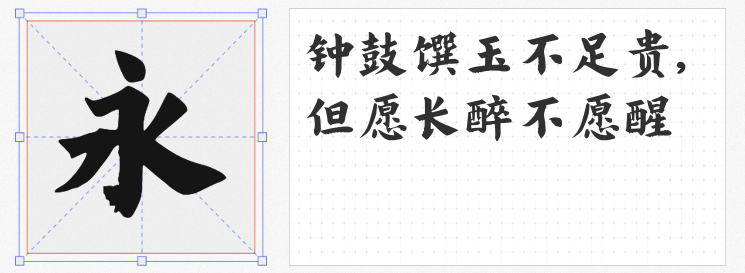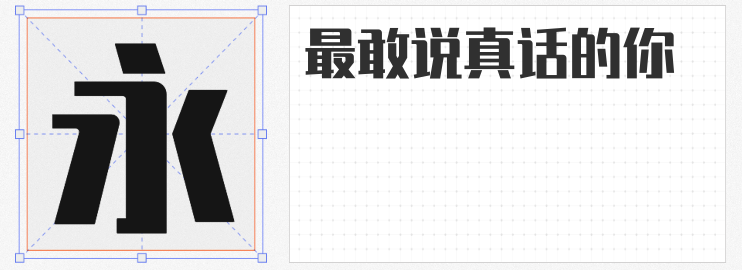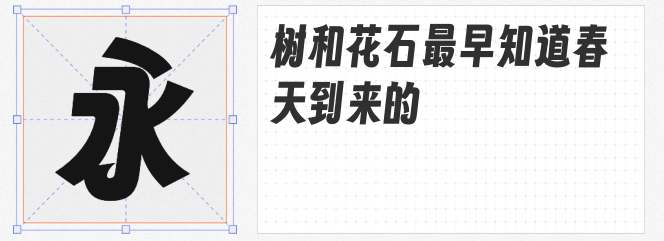
在短视频与媒体内容竞争激烈的今天,一个吸引眼球的封面设计往往能决定内容的点击率与传播力。而字体,作为封面设计中的灵魂元素,其选择至关重要。今天,我们精心挑选了四款既免费商用又极具创意的字体,助你轻松打造出令人过目难忘的封面作品。
这款字体笔触浑厚,笔画曲折有致,个性鲜明而不失刚柔并济之美。直角与圆角的巧妙搭配,让字体在婉转中透露出落落大方的气质,非常适合用于需要展现力量感与现代感的封面设计。
2. 乡立方黑体
灵感源自乡村发展的时代感刷墙字体,乡立方黑体在保留乡村韵味的同时,融入了现代设计理念。它通过对笔形、部件及字面空间的创新设计,构建出了一款既符合乡村形象又具时代感的全新字体,为乡村主题内容的封面设计提供了独特选择。
3. 程荣光刻楷
作为一款免费商用的楷体字体,程荣光刻楷以其工整秀丽、韵味悠长的特点,赢得了众多设计师的青睐。它适用于需要展现文化底蕴与雅致氛围的封面设计,让内容在传递信息的同时,也能感受到一份来自书法的宁静与美好。
4. 字魂扁桃体
基于得意黑进行创意升级,字魂扁桃体在保留得意黑标志性倾斜与弯弧处理的基础上,通过加粗字重、加宽字身以及特色喇叭口设计,让字体更加饱满有力,个性十足。这款字体既温和又时髦,非常适合用于追求时尚感与创意表达的封面设计。
这四款免费商用创意字体,各具特色,定能为你的短视频与媒体封面设计增添无限魅力!